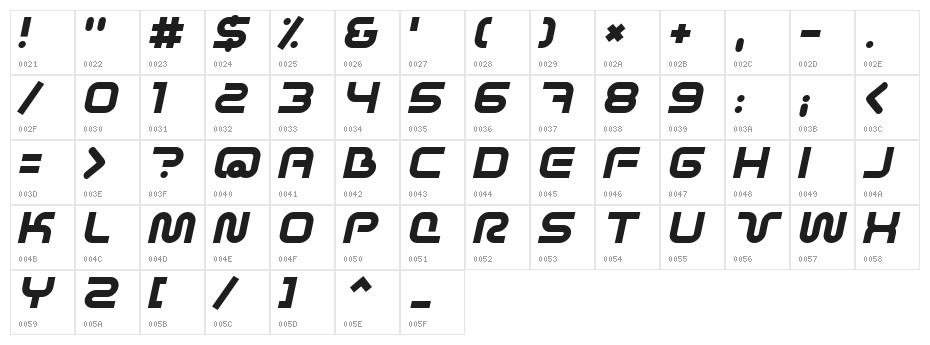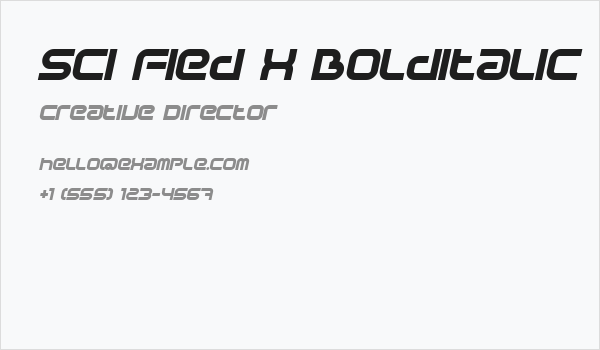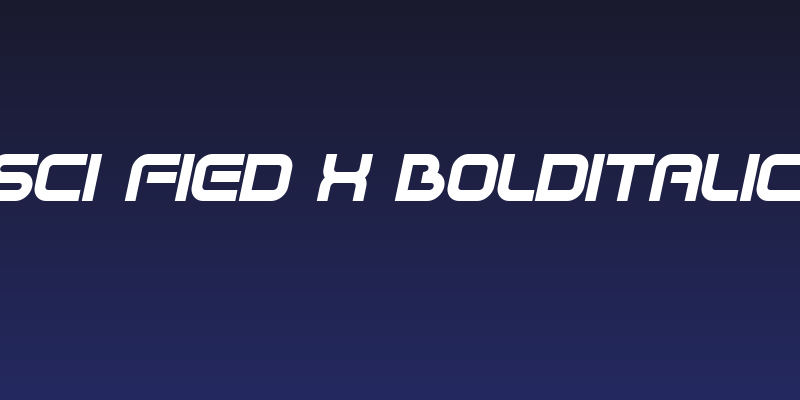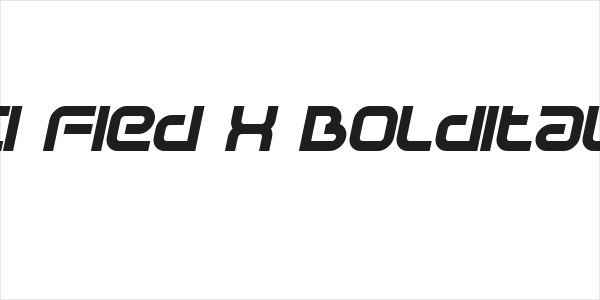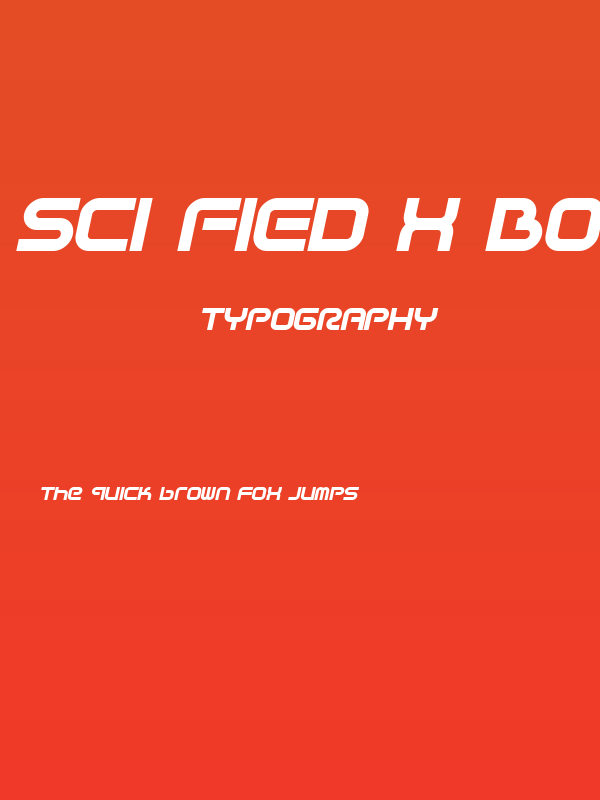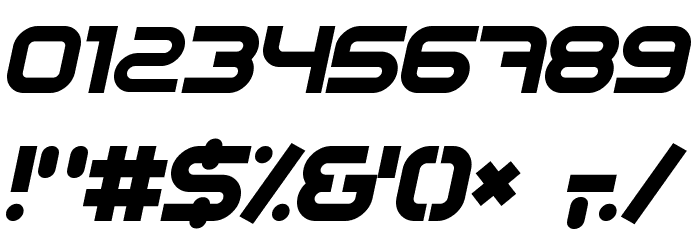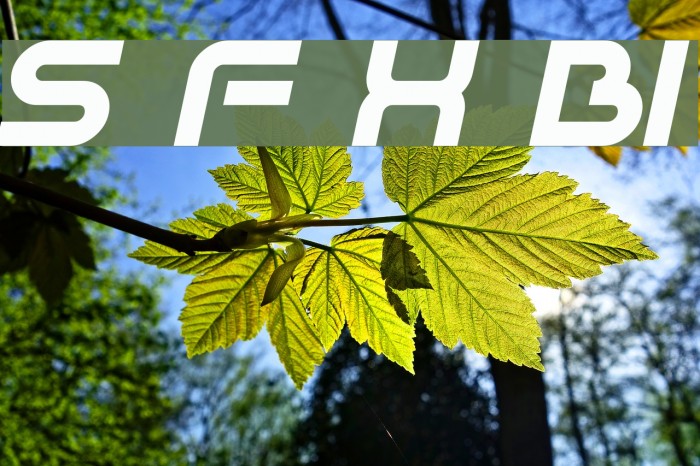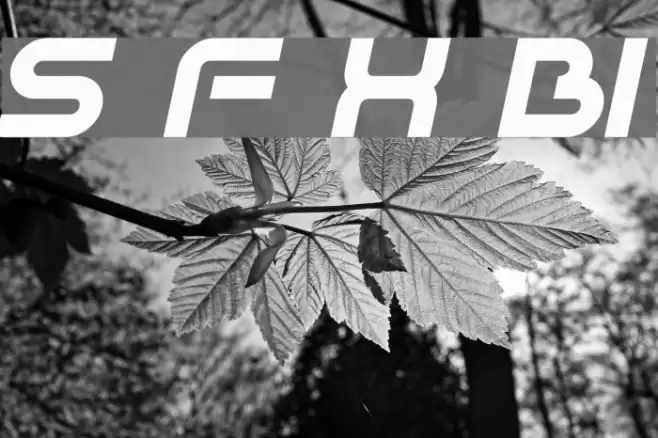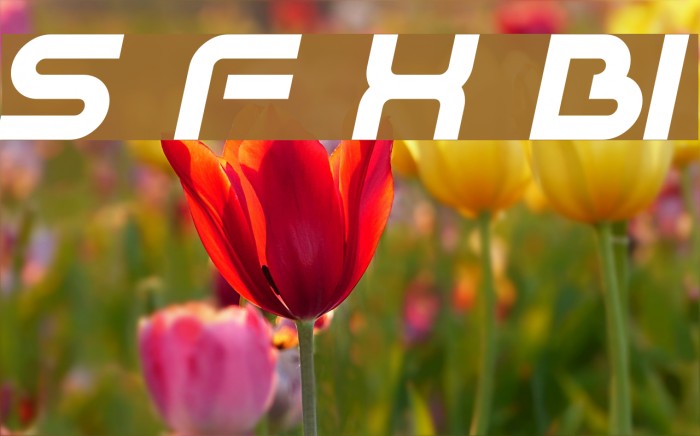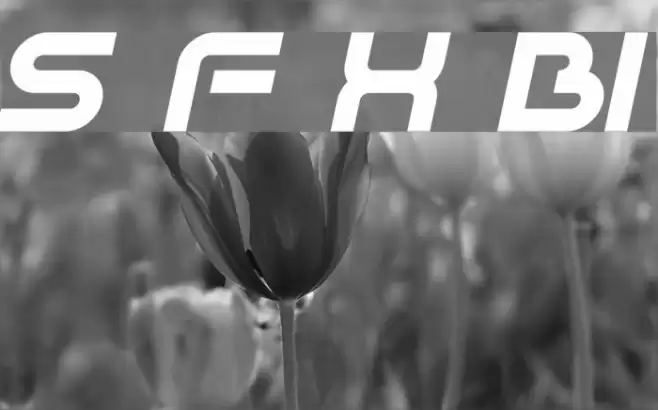
Sci Fied X BoldItalic Font
✎ Futuristic
| Vorgeschlagene Projekte | Ideal for sci-fi themed posters, video game graphics, technology branding, and futuristic web design. |